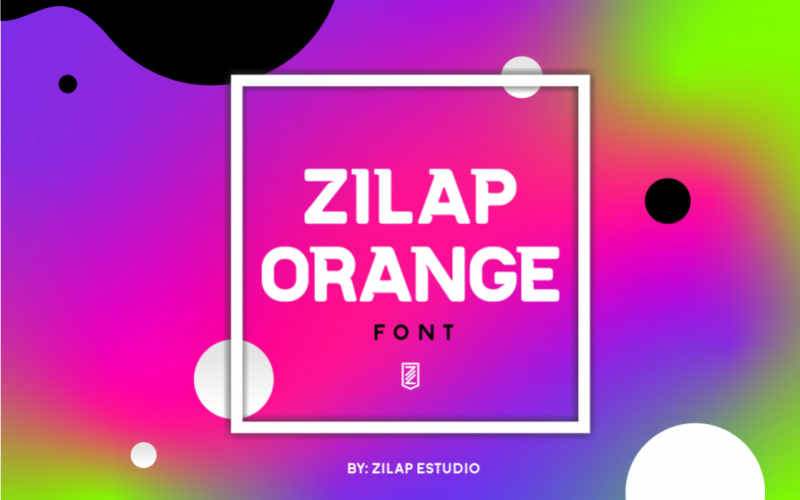
Zilap Orange Sans Serif Font
Zilap Orange Sans Serif Font est une police de caractères moderne aux bords arrondis, idéale pour les logos, les titres, les affiches, les vêtements, les emballages de produits, les marques, les magazines, etc. Cette police comprend des lettres majuscules, des chiffres, des symboles et est multilingue. C’est une source fraîche et créative, qui s’adapte aux grands besoins de grafica.